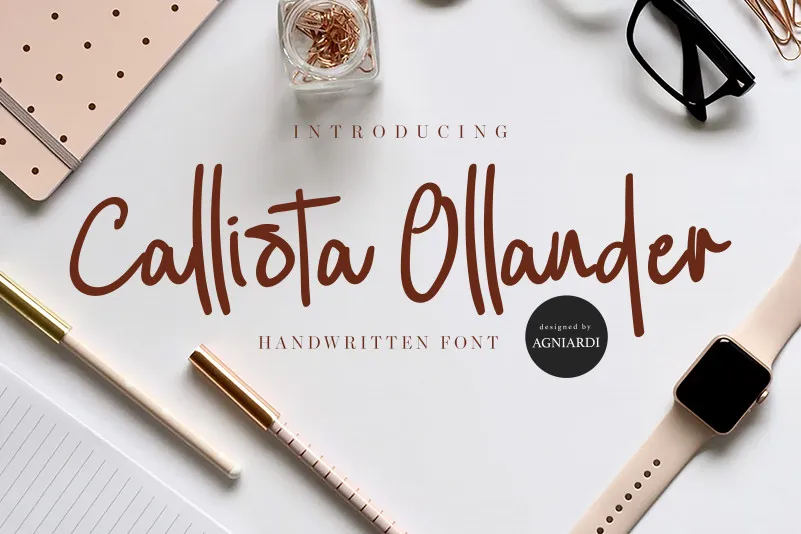
Callista Ollander Script Font – Download Grátis
A Callista Ollander Script Font é uma elegante fonte escrita a mão que traz uma sensação autêntica para qualquer projeto design. Feita sobretudo para quem busca um estilo moderno e sofisticado, esta fonte irá transformar até os mais simples projetos em verdadeiras obras de arte. Seu charme natural e personalidade única tornam-a perfeita para aqueles que desejam uma mistura sutil entre elegância e autenticidade em suas criações digitais. Com a Callista Ollander Script Font, você terá à disposição um recurso gráfico poderoso capaz de dar identidade e personalidade ao seu design. Seja para criar letras impecavelmente legíveis em aplicativos móveis ou para adicionar uma pitada única no layout de sua próxima publicação digital, esta fonte será o complemento perfeito à sua paleta de recursos gráficos.